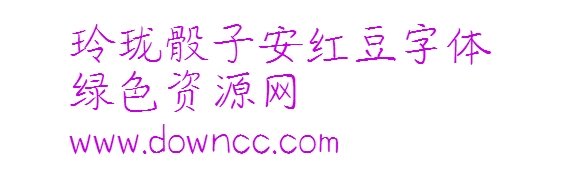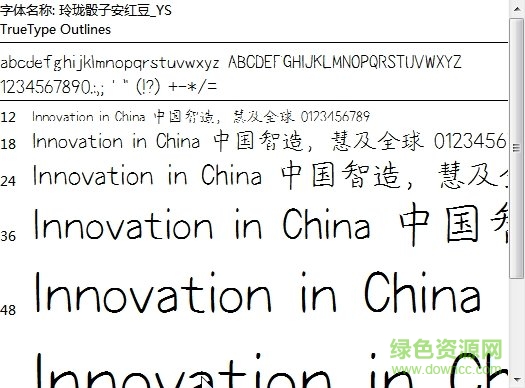
玲瓏骰子安紅豆ttf字體是一款有著清婉秀氣古色韻味的手寫(xiě)字體,無(wú)論是中文還是英文都有著舒緩工整的造型,給你極佳的閱讀體驗(yàn),喜歡本字體的朋友就可以來(lái)綠色資源網(wǎng)免費(fèi)下載哦!
玲瓏骰子安紅豆字體是手機(jī)qq上使用的唯美藝術(shù)字體,字體細(xì)致婉約如同訴說(shuō)著綿綿情意,造型疏松而不壓抑,具有很高的文字辨識(shí)度,可以適用于印刷排版、海報(bào)設(shè)計(jì)、創(chuàng)意廣告等領(lǐng)域。